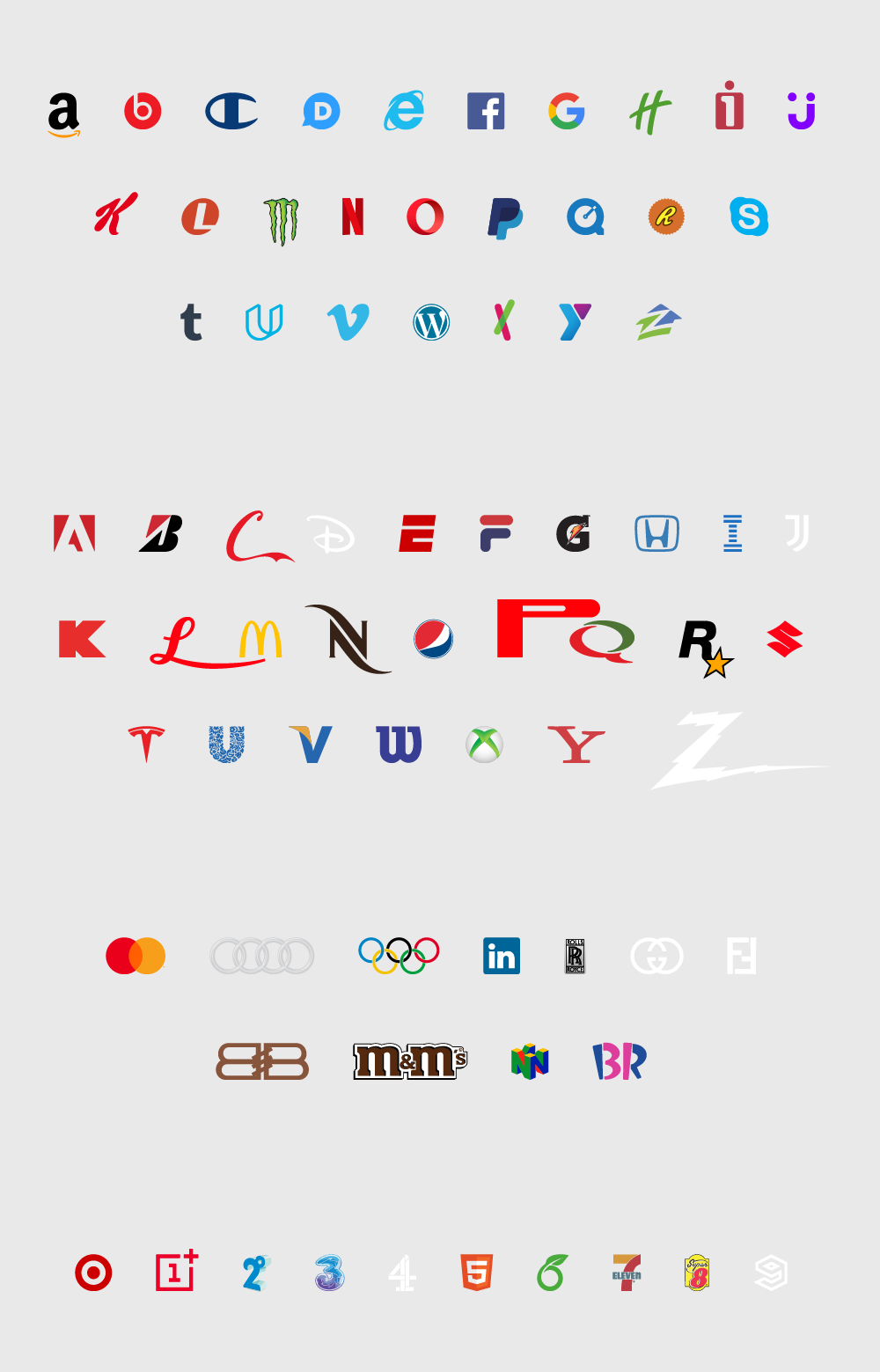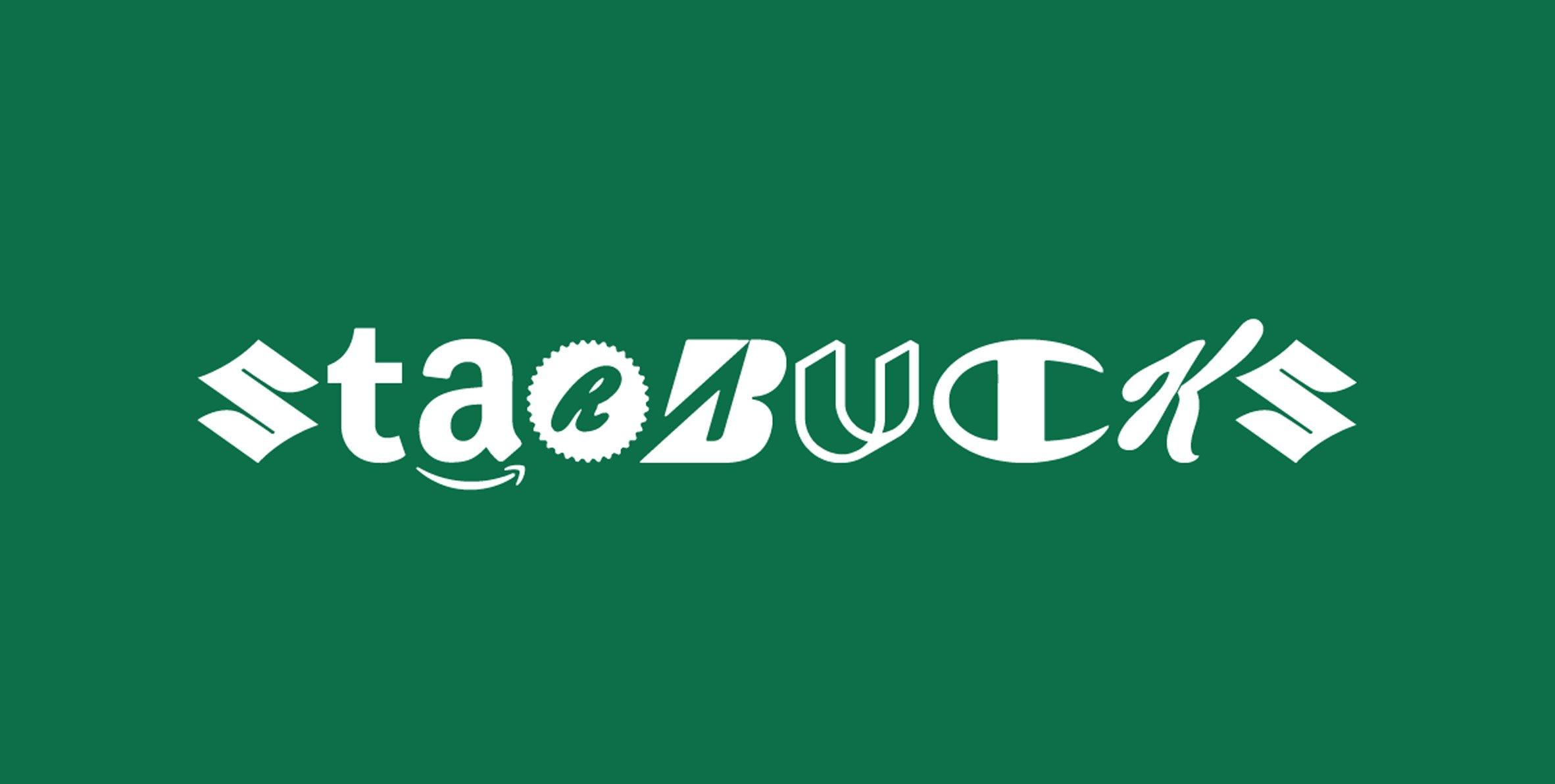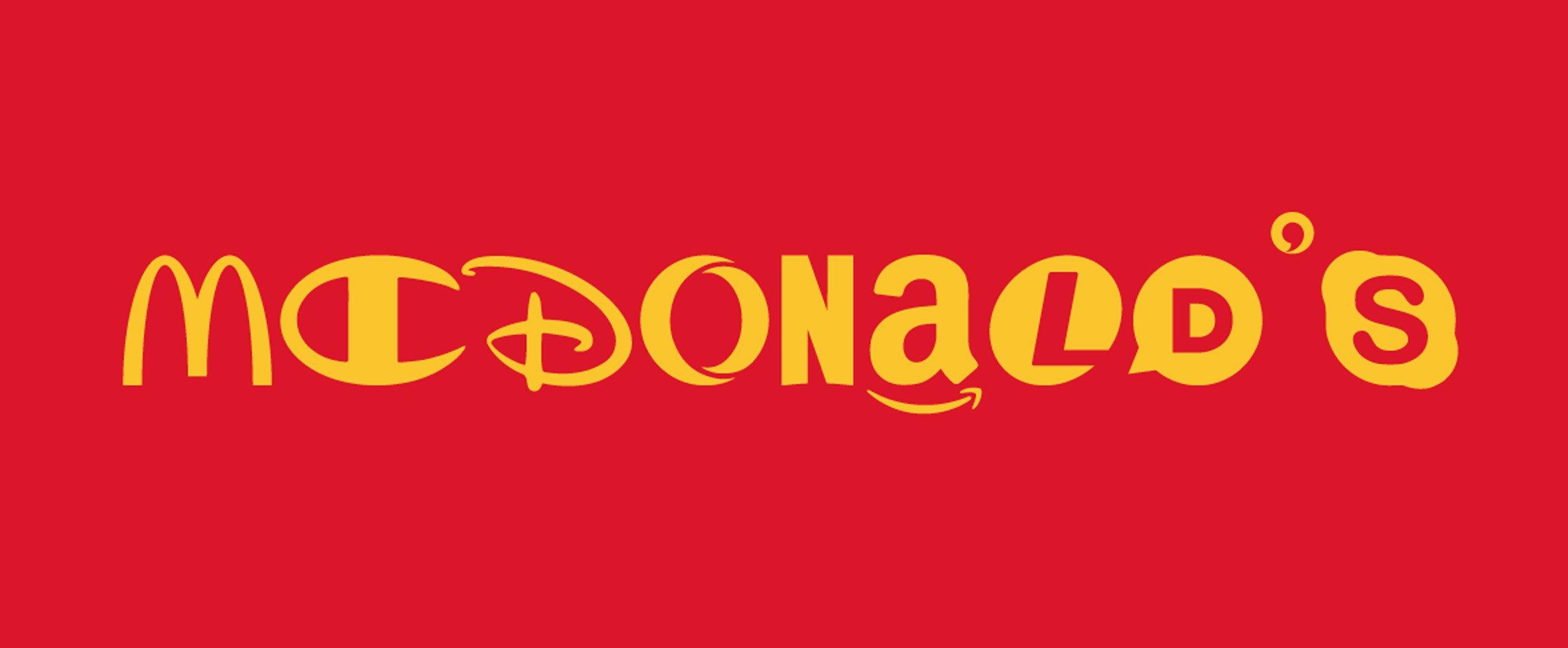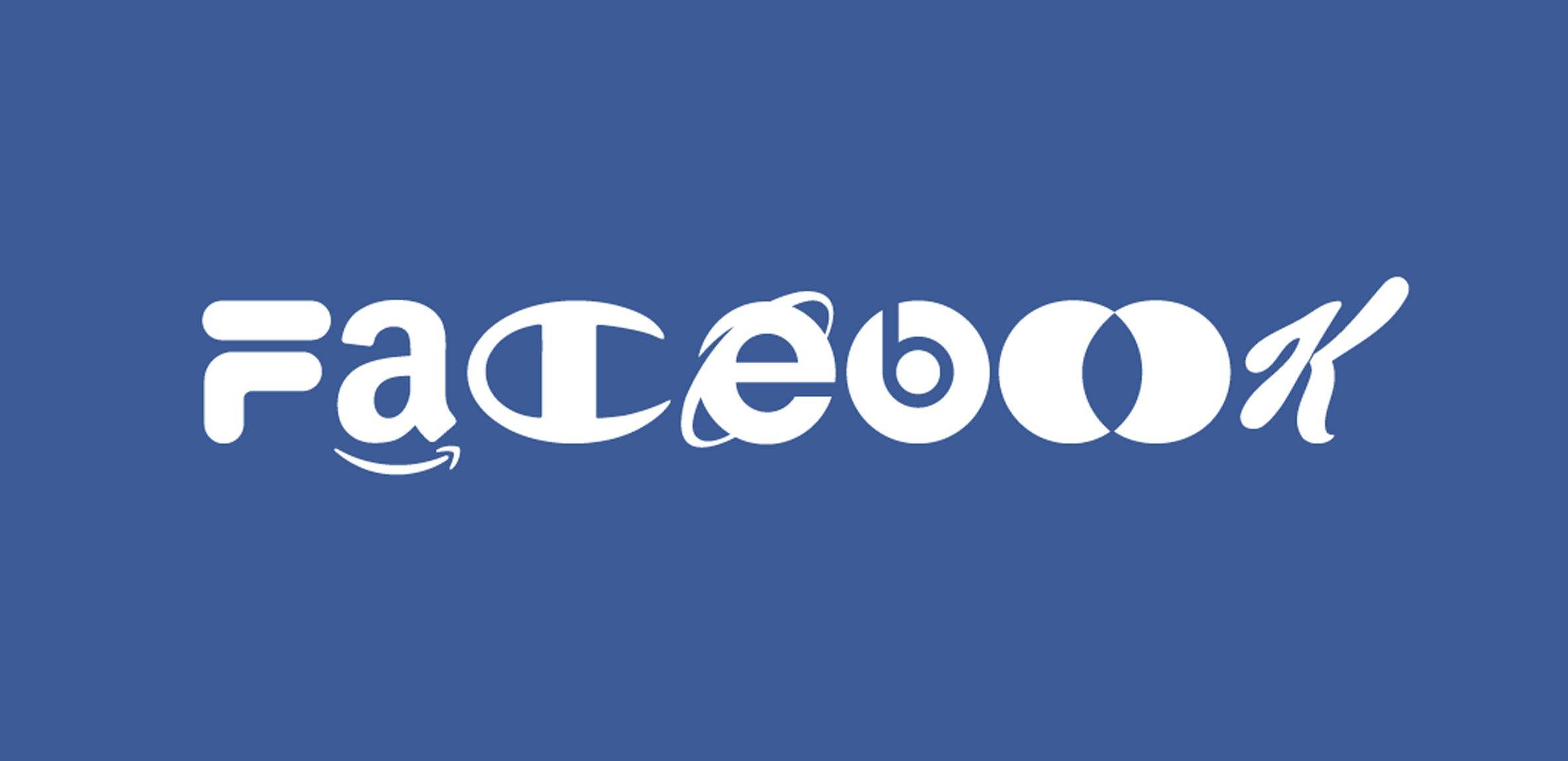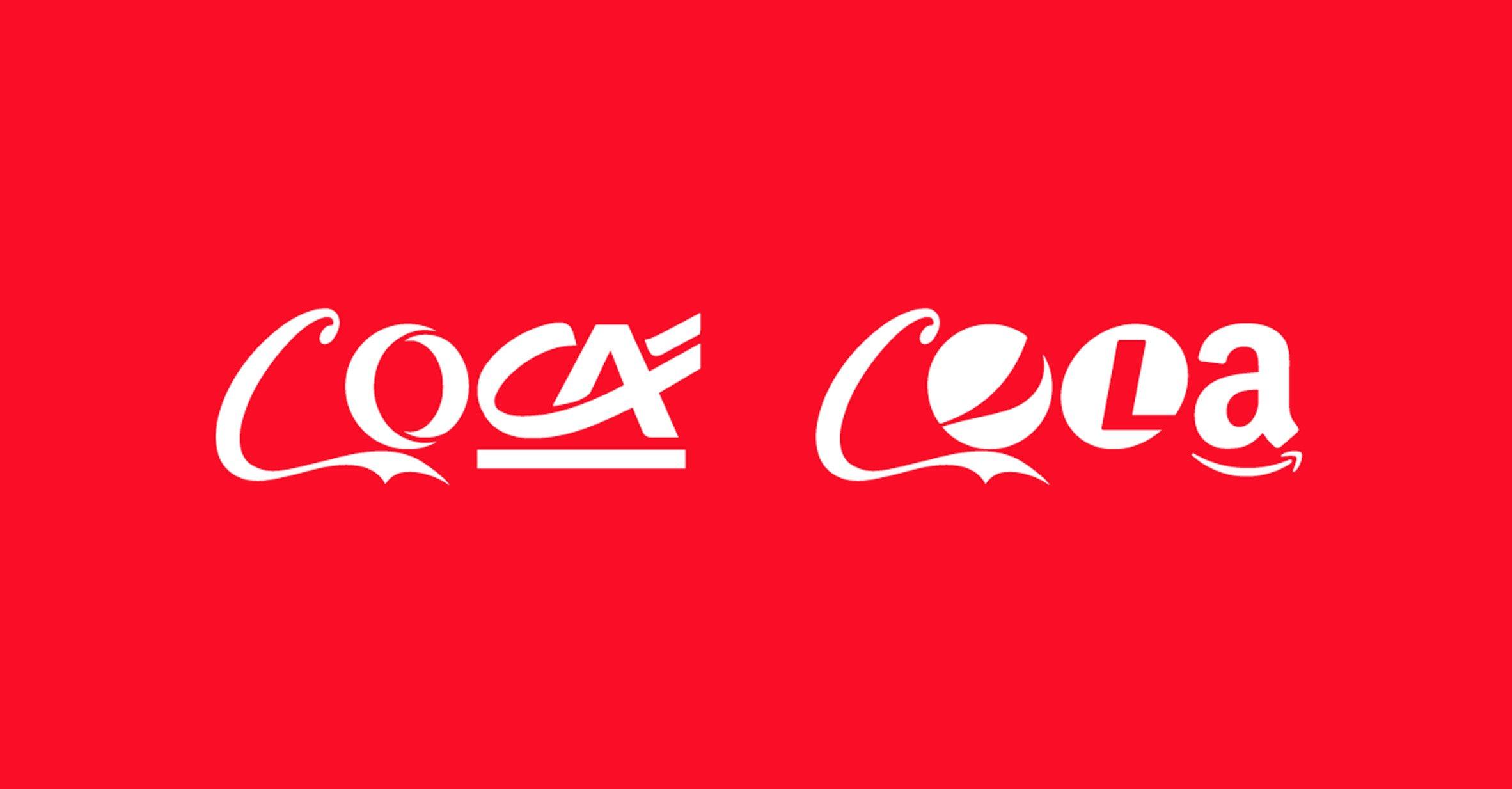
Il sito web dello studio creativo Hello Velocity recita "Hello Velocity creates thought-provoking internet experiences", e da qui si può intuire l'estro e la creatività del team dietro a questa agenzia con sede a New York e Boston. Uno dei suoi ultimi progetti, infatti, consiste nella creazione di un font unico nel suo genere, che utilizza i loghi o le forme distintive di marchi famosi in tutto il mondo, come Amazon, Facebook o Netflix, chiamato Brand New Roman. Una specie di parodia del celebre e classico carattere Times New Roman, creata partendo dai tratti immediatamente distintivi di brand noti a chiunque. Ogni lettera dell'alfabeto, sia in minuscolo che maiuscolo, corrisponde a un determinato logo, oltre ad alcune combinazioni particolari.
Il font è stato creato per ironizzare sul potere e sulla grande influenza di questi brand a livello globale. "Questo stadio del capitalismo è piuttosto strano", ha dichiarato il direttore creativo di Hello Velocity, Lukas Bentel. "Sembra il momento giusto per prenderlo in giro!". Al giorno d'oggi, infatti, i brand possono essere ovunque nel mondo e sono "affamati di attenzioni".
Il nuovo carattere tipografico di Hello Velocity li fa sembrare allo stesso livello, facendogli perdere tutte le connotazioni di potere e influenza di cui si servono ogni giorno per attirare i consumatori. La densità che si crea scrivendo una parola con il font, infatti, annulla tutte le associazioni legate all'identità di brand, che il logo normalmente comunica.
In fase di progettazione, lo studio ha rivelato che il team di design ha voluto utilizzare solo loghi che potevano apparire come elementi di branding autonomi, in modo che con un logo composto da una singola lettera o un simbolo che gli potesse assomigliare potesse immediatamente comunicare un collegamento tra lettera del font e brand a cui fa riferimento. Il progetto di design si è delineato dopo numerosi tentativi per trovare il set di lettere che funzionasse meglio, anche per rendere il font quanto più leggibile possibile.
Il team ha anche provato a restringere ogni lettera ai loghi che consideravano più riconoscibili, ma è stato necessario fare qualche eccezione. "Abbiamo rotto queste regole in alcune occasioni, quando era diventato impossibile soddisfarle. Ad esempio, vi sfido a pensare a un'azienda che usa la lettera I come un logo autonomo e leggibile!".
Sempre mediante il suo direttore creativo, in un'intervista a Dezeen lo studio ha dichiarato di essere sempre stato interessato a sperimentare, criticare e fare satira sui sistemi economici e sul panorama commerciale, in particolare sul web. "Credo che il Brand New Roman sia esteticamente efficace, e ciò fa capire tutto il tempo, i soldi e la progettazione dietro alla creazione di ciascuno di questi loghi", ha concluso Bentel.
Il font include al suo interno colossi come McDonald's, Google o Tesla, ma anche brand meno conosciuti, almeno al panorama europeo. Non mancano combinazioni di lettere curiose, come la doppia "g" che forma il logo di Gucci o la doppia "f" per Fendi. Molto curioso cosa succede con la lettera "o": mentre con la singola lettera minuscola compare il logo del browser Opera e con quella maiuscola quello di Pepsi, se si digita due "o" compare quello di Mastercard, con quattro quello di Audi e con cinque si può ammirare il logo dei cinque anelli dei giochi olimpici.
Di seguito abbiamo svelato tutte le corrispondenze lettera-logo.
b - Beats by Dr Dre | B - Bridgestone | bb - Balenciaga | br - Baskin-Robbins
e - Internet Explorer | E - ESPN
f - Facebook | F - Fila | ff - Fendi
g - Google | G - Gatorade | gg - Gucci
h - Holiday Inn | H - Honda
i - Iomega | I - IBM | in - Linkedin
l - Lear Corporation | L - Leica
m - Monster | M - McDonald's | mm - M&M's
n - Netflix | N - Nespresso | nn - Nintendo 64
o - Opera | O - Pepsi | oo - Mastercard | oooo - Audi | ooooo - Olimpiadi
r - Reese's | R - Rockstar | rr - Rolls Royce
0 - Target | 1 - OnePlus | 2 - 2degrees Mobile | 3 - Three | 4 - Channel 4 | 5 - HTML 5 | 6 - Overleaf | 7 - 7Eleven | 8 - Super 8 | 9 - 9GAG
"Al giorno d'oggi, i brand sono inevitabilmente presenti ovunque e affamati d'attenzione" - Lukas Bentel, Creative Director di Hello Velocity